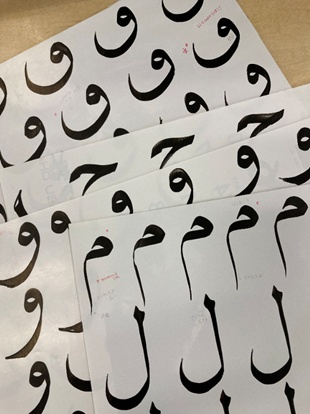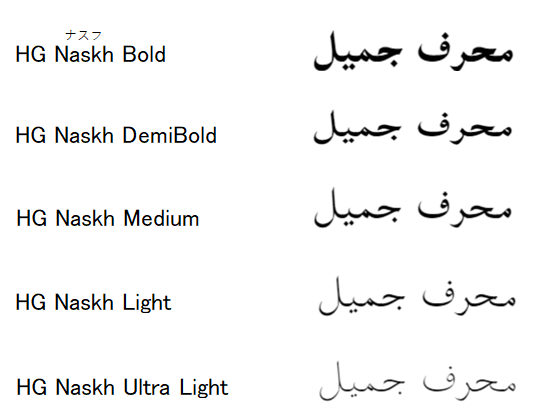
HG Naskh(ナスフ)
- コーラン(イスラム教の聖典)を書き写すために誕生したものです。
- 流線状で筆記に適した書体をナスヒー体(Naskhは筆写という意味)といいます。
- アラビア語ネイティブの方になじみのある書体である
- 装飾が小さくて文章が読みやすい
- 印刷用活字書体やiOSやAndroidでのアラビア語システムフォント、webなど画面表示においても広く普及している
- 実際にアラビア書道で使用している筆を使って元になる文字(字母といいます)を一つ一つ手書きで制作し、それを元にTrue type Font に仕上げました。
- HG Naskhは、1文字ごとのデザインとしては伝統的な形ではありますが、文字のつながり方については難しさを排除して読みやすくしています。
- また、完成した文字についてはネイティブの方に自然な字形との評価をいただいております。
よく目にするもの
(例)交通機関の案内表示やドキュメント